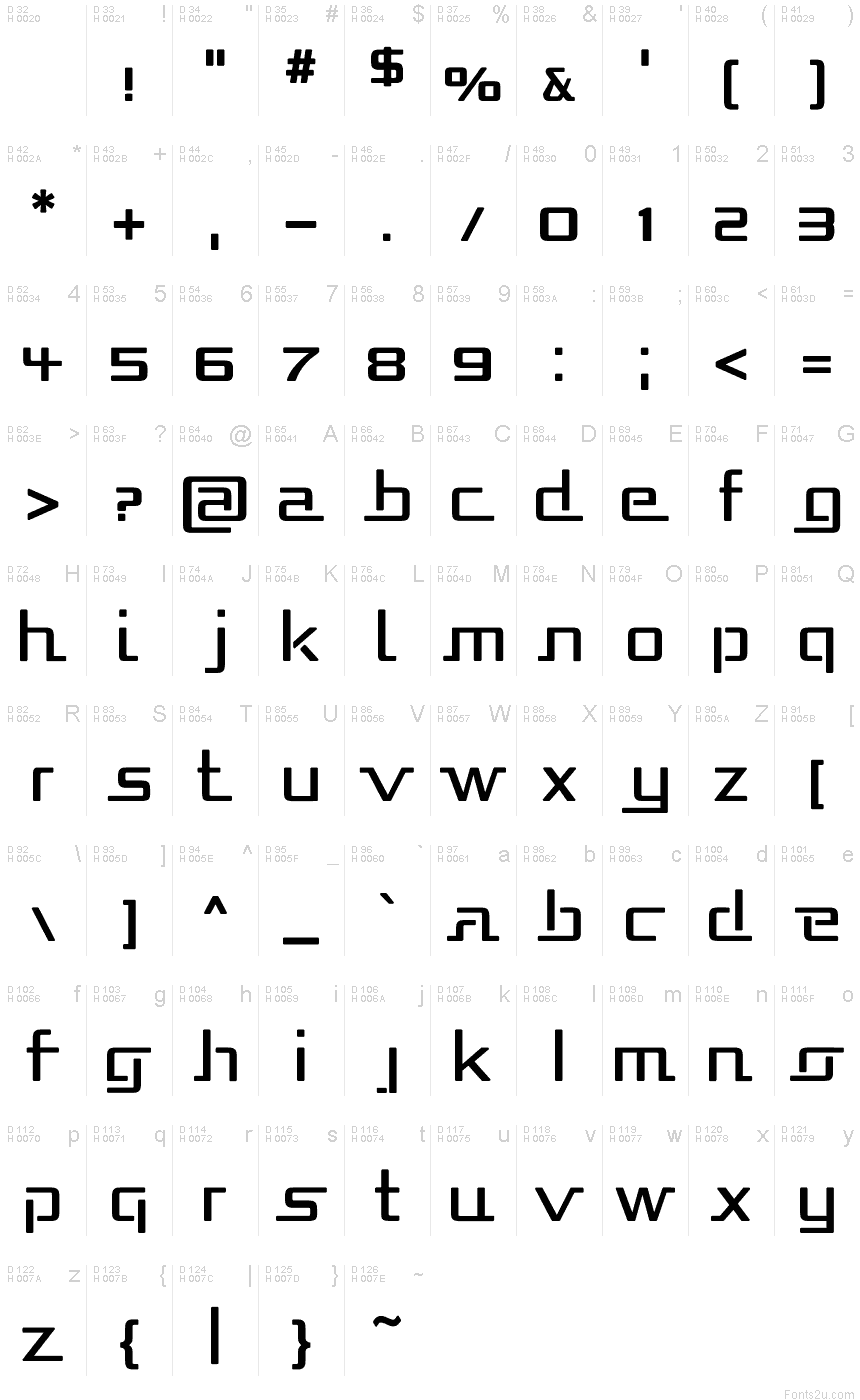
Republika من Apostrophe هو خط عرض مستقبلي يتميز بإيقاع تقني أنيق. تتحرك الحروف عبر مسارات مربعة ومستديرة تبدو وكأنها مصممة بدقة وانسيابية، مع منحنيات مفتوحة وزوايا مقصوصة وبعض اللمسات الرأسية العالية التي تضفي على الكلمات مظهرًا إلكترونيًا كلاسيكيًا يذكرنا بالدوائر الكهربائية.
يندمج هذا الخط بشكل طبيعي في ملصقات الخيال العلمي، وتغليف المنتجات الموسيقية، وتصاميم ألعاب الفيديو، وعناوين العروض، حيث ترغب في أن تنقل الحروف أجواء التصميم. وبما أنه خط مجاني، فإن Republika يعد خيارًا ممتازًا للشعارات، وعناوين الواجهات، ومقاطع الموشن جرافيك القصيرة، إذ تمنح تلك الروابط المتصلة والخطوط الرأسية البارزة حتى الكلمات القصيرة إحساسًا بالحركة والديناميكية.